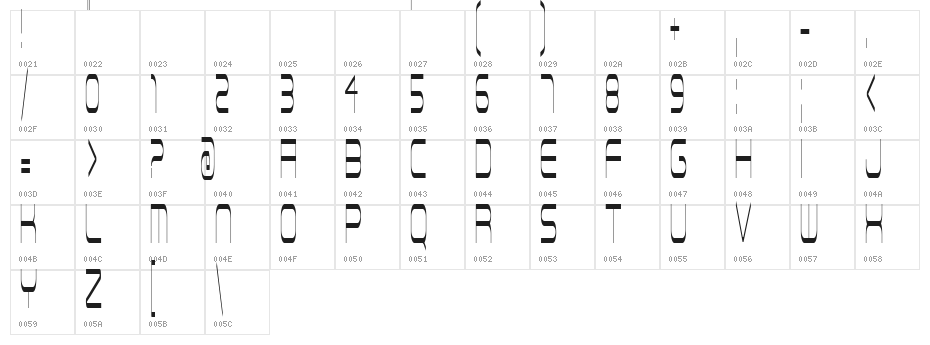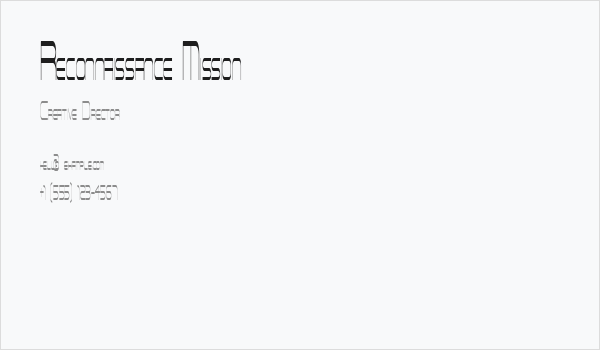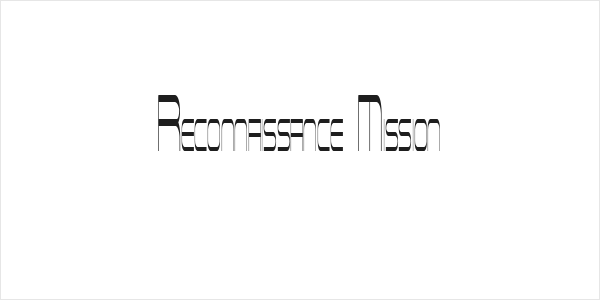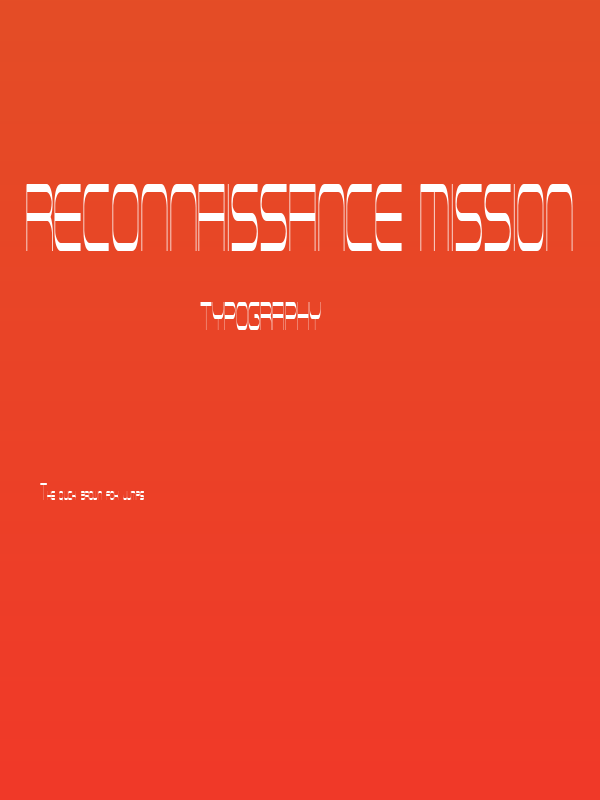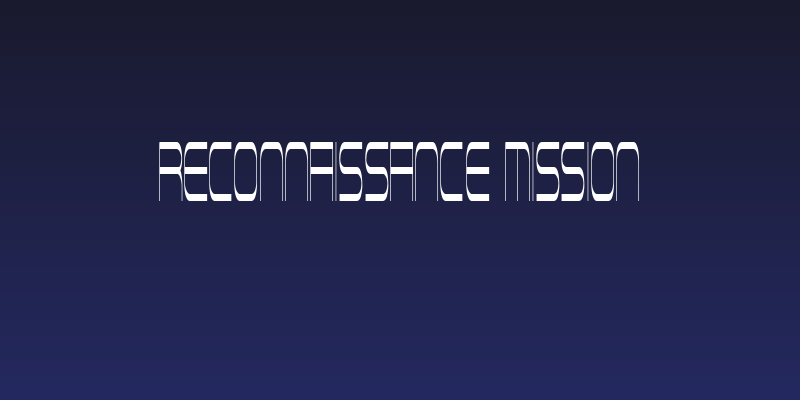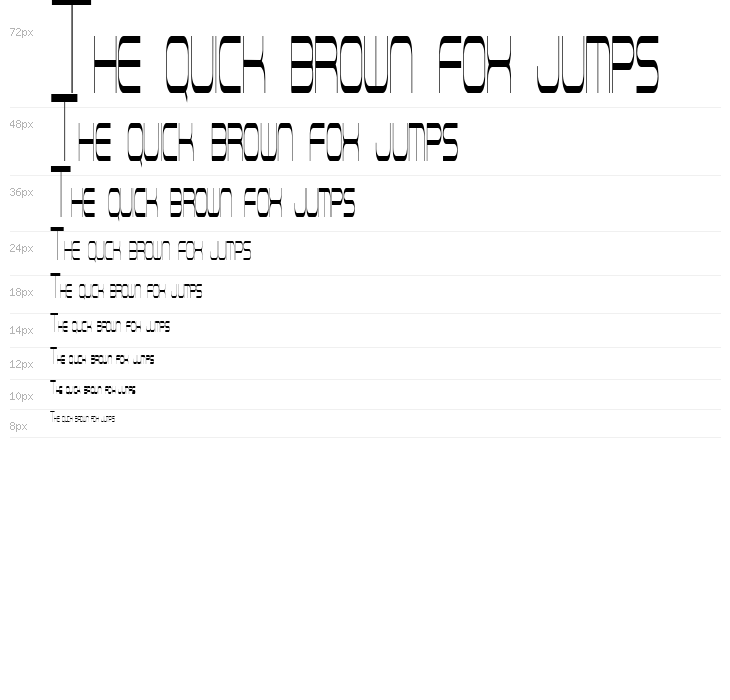
Reconnaissance Mission Font
| Progetti proposti | Ideal for technology branding, sci-fi movie posters, video game titles, and modern digital interfaces. |